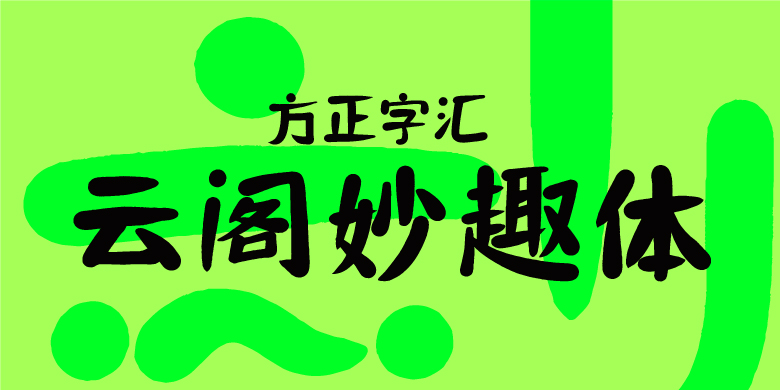
方正字汇-云阁妙趣体
方正字汇-云阁妙趣体,这款字体结构工整、笔画清晰,兼顾美观与易读性,适用于标题、正文、海报、包装、LOGO 等多种场景。字形优雅稳定,风格百搭耐看,适配日常排版与创意设计,让文字呈现更舒适、更具质感。方正字汇-云阁妙趣体一笔一画,皆是细节,以均衡的比例、流畅的线条打造舒适视觉体验,字形端正大气,风格简约现代。无论是商业设计、品牌宣传还是日常排版,都能轻松驾驭,让文字更有格调与力量。方正字汇-云阁妙趣体字体下载。
与传统的书法书写方式不同,云阁妙趣体整套字体应用数位板和软件创作,在视觉上传达看似规整却又不拘的独特氛围,尝试创新的书写形态。笔画干净利落,可爱生趣,线条书写流畅顺滑,年轻时尚,具有较高的识别度;后期可以运用三维效果、渐变、图案填充等手法,使字体更加生动、多变和引人注目,并可以广泛应用于各种媒介。